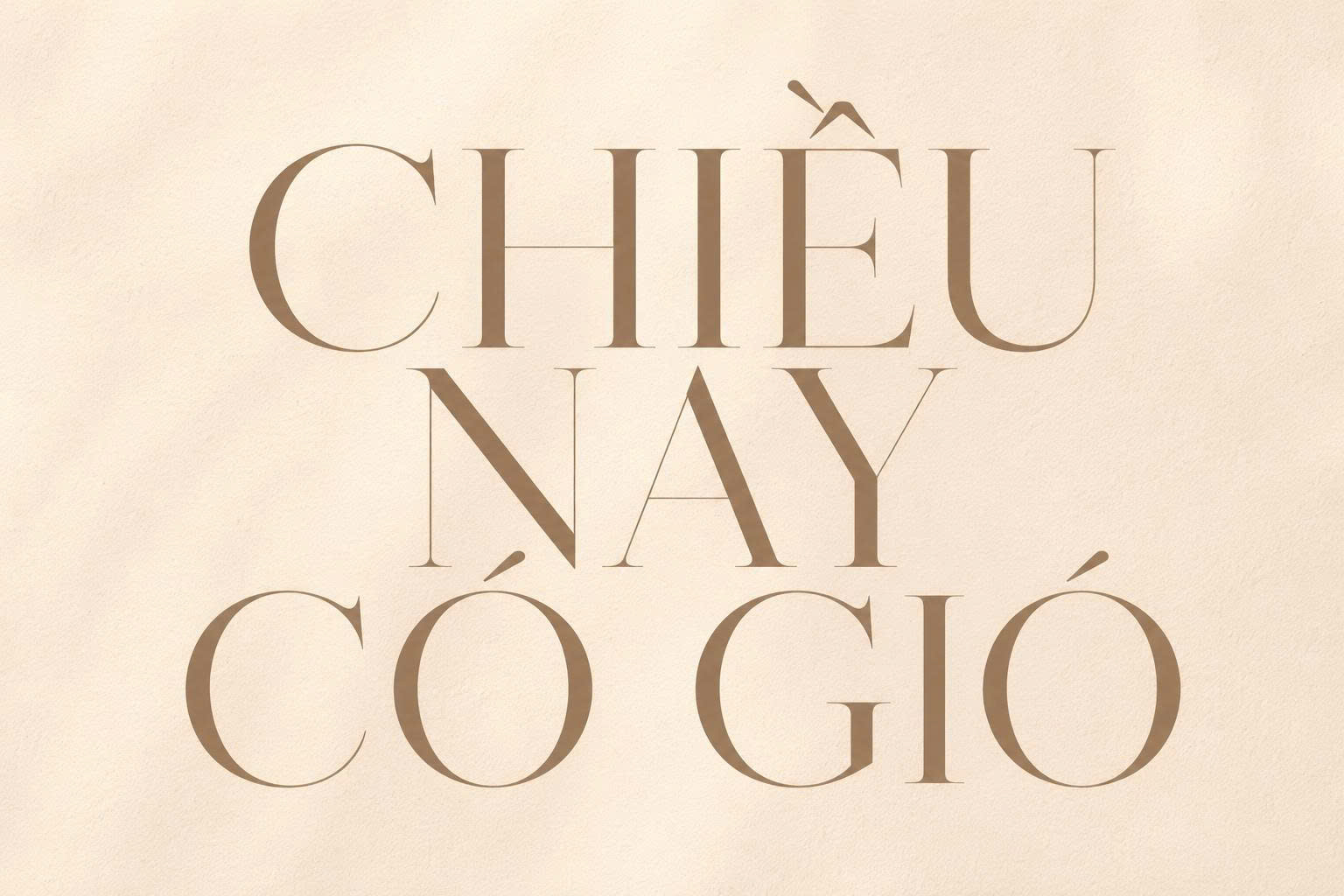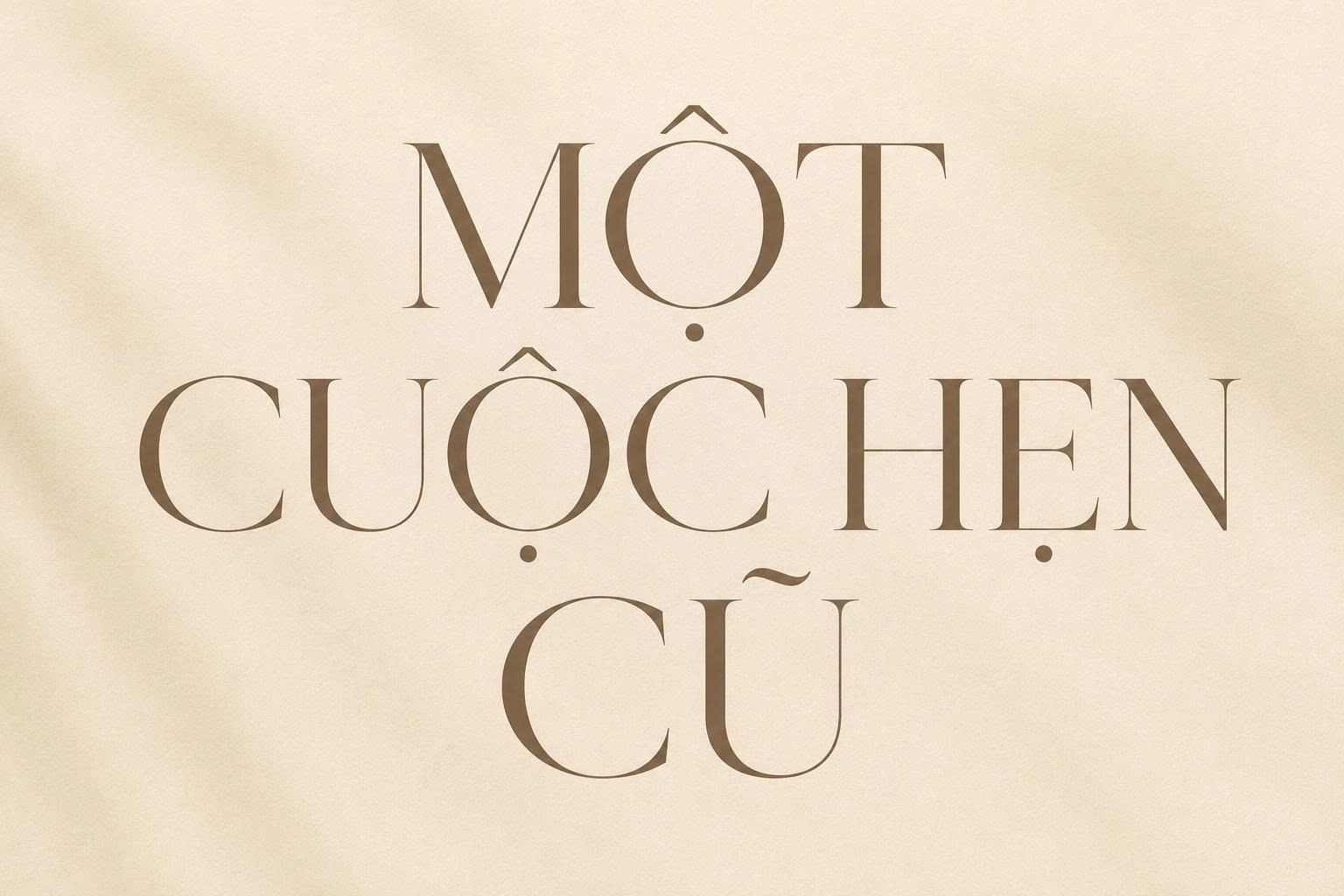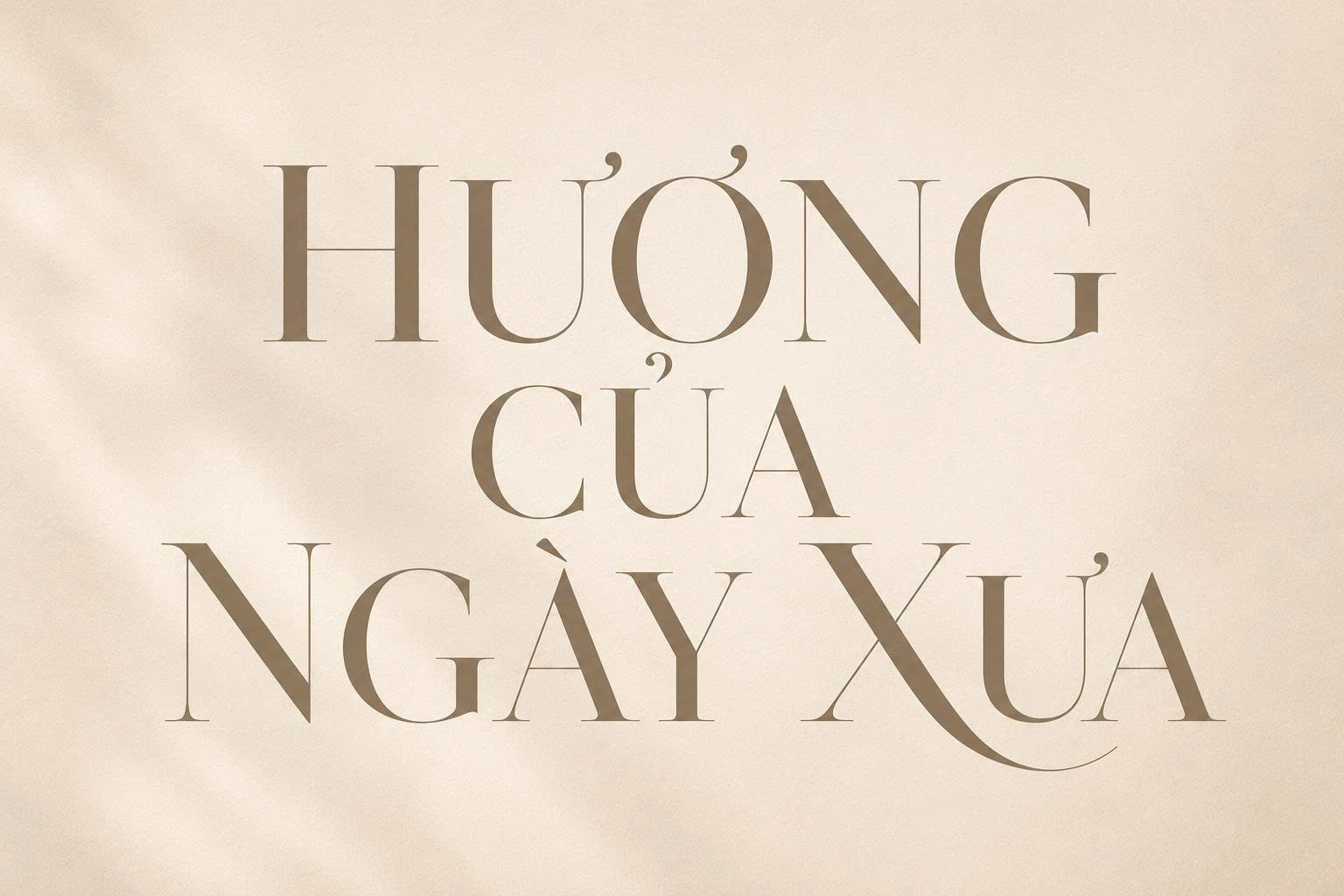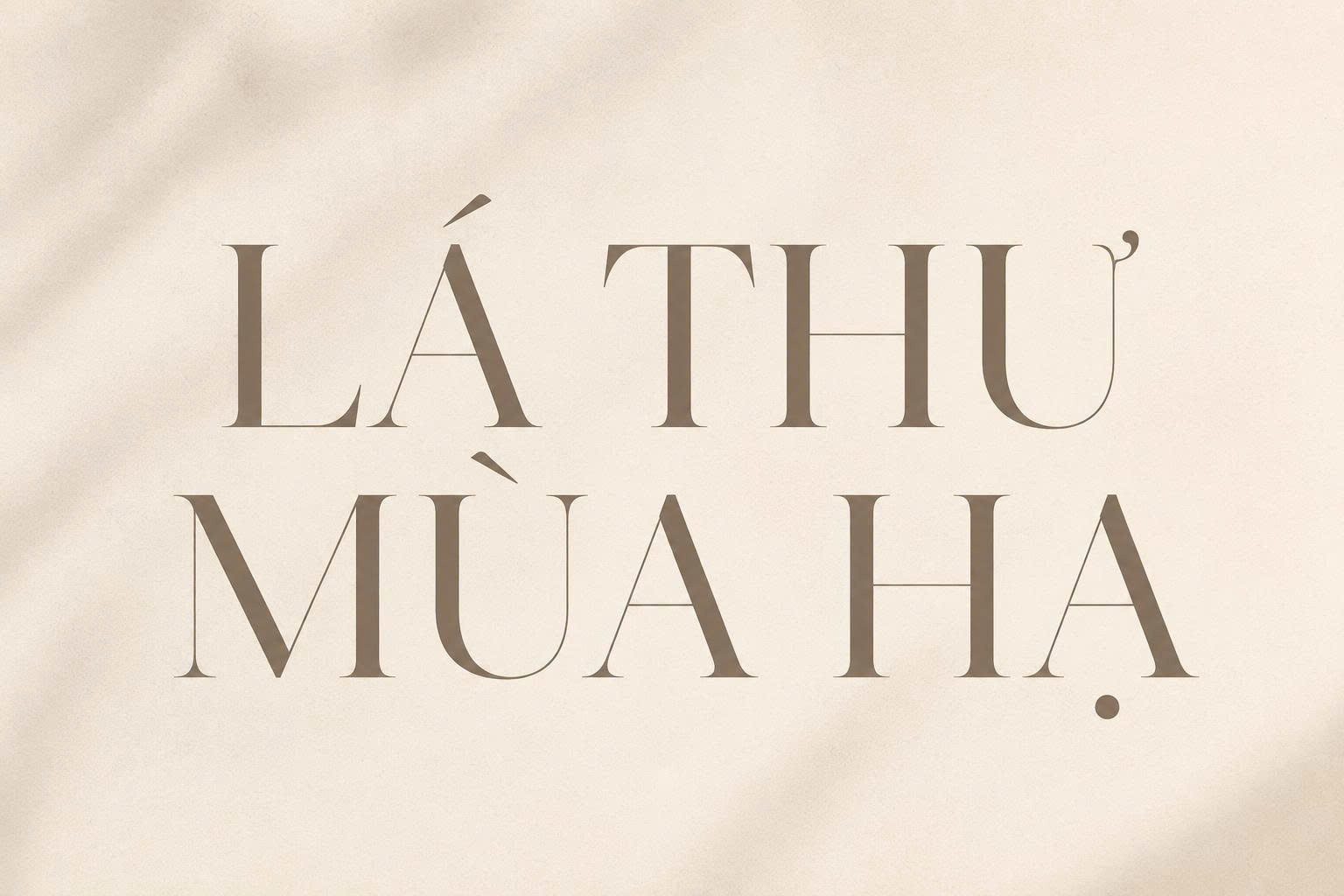
Font Việt hóa SVN Conqueror Didot là bộ phông chữ thuộc dòng Modern Serif (có chân hiện đại) nổi tiếng với vẻ đẹp thanh lịch, sắc sảo và đẳng cấp. Được truyền cảm hứng từ những trang tạp chí thời trang danh tiếng, SVN Conqueror Didot sở hữu độ tương phản nét thanh đậm cực lớn, mang lại hơi thở của sự sang trọng cho mọi bản thiết kế. Doozypack.vn chia sẻ link tải font Didot Việt hóa chuẩn, giúp bạn sở hữu bộ font chữ tiếng Việt SVN-Conqueror Didot trọn vẹn để nâng tầm nhận diện thương hiệu và bao bì cao cấp.
Đặc điểm thẩm mỹ của font chữ tiếng Việt SVN-Conqueror Didot
Didot không chỉ là một phông chữ, nó là biểu tượng của phong cách Typography thời thượng, thường xuyên được các nhãn hàng Luxury trên thế giới ưu ái lựa chọn.
font Didot Việt hóa phong cách sang trọng
Độ tương phản nét thanh đậm cực kỳ sắc sảo
Đặc trưng lớn nhất của bộ svn didot là sự đối lập mạnh mẽ giữa những nét dọc dày dặn, chắc chắn và những nét ngang, nét nối thanh mảnh như sợi tóc (hairline). Sự kết hợp này tạo nên một hiệu ứng thị giác vô cùng tinh tế, gợi nhắc đến phong cách cổ điển của châu Âu nhưng vẫn mang tính ứng dụng cao trong đồ họa hiện đại.
Hệ thống dấu tiếng Việt được tinh chỉnh hoàn hảo
Nỗi đau thường gặp của designer khi tải font Didot bản gốc là các dấu thanh tiếng Việt thường bị thô, đè nét hoặc sai lệch vị trí. Tuy nhiên, phiên bản SVN Conqueror Didot tại Doozypack.vn đã được tối ưu hoàn toàn. Các dấu sắc, huyền, hỏi, ngã, nặng được thiết kế thanh mảnh đồng nhất với cấu trúc chữ, đảm bảo văn bản tiếng Việt luôn đạt độ thẩm mỹ cao nhất trên các ấn phẩm in ấn chuyên nghiệp.
mẫu font chữ SVN Conqueror Didot thanh mảnh và sắc nét
03 Ứng dụng của SVN Conqueror Didot trong ngành in ấn bao bì
Tại xưởng sản xuất của Doozypack.vn, SVN Conqueror Didot luôn là “ngôi sao” cho các dòng sản phẩm yêu cầu sự trang trọng:
• Bao bì mỹ phẩm & Nước hoa: Nét chữ sắc sảo của Didot cực kỳ phù hợp cho các dòng sản phẩm chăm sóc sắc đẹp cao cấp, tạo cảm giác sạch sẽ và quý phái.
• Thiết kế Logo thương hiệu thời trang: Giúp bộ nhận diện toát lên vẻ thời thượng, gợi nhắc đến phong cách của các tạp chí lớn như Vogue hay Harper’s Bazaar.
• Hộp quà tặng doanh nghiệp: Tên thương hiệu in bằng font Didot kết hợp với kỹ thuật ép kim nhũ vàng trên nền hộp tối màu sẽ tạo nên một diện mạo vô cùng đẳng cấp.
font chữ Didot tiếng Việt trên bao bì mỹ phẩm cao cấp